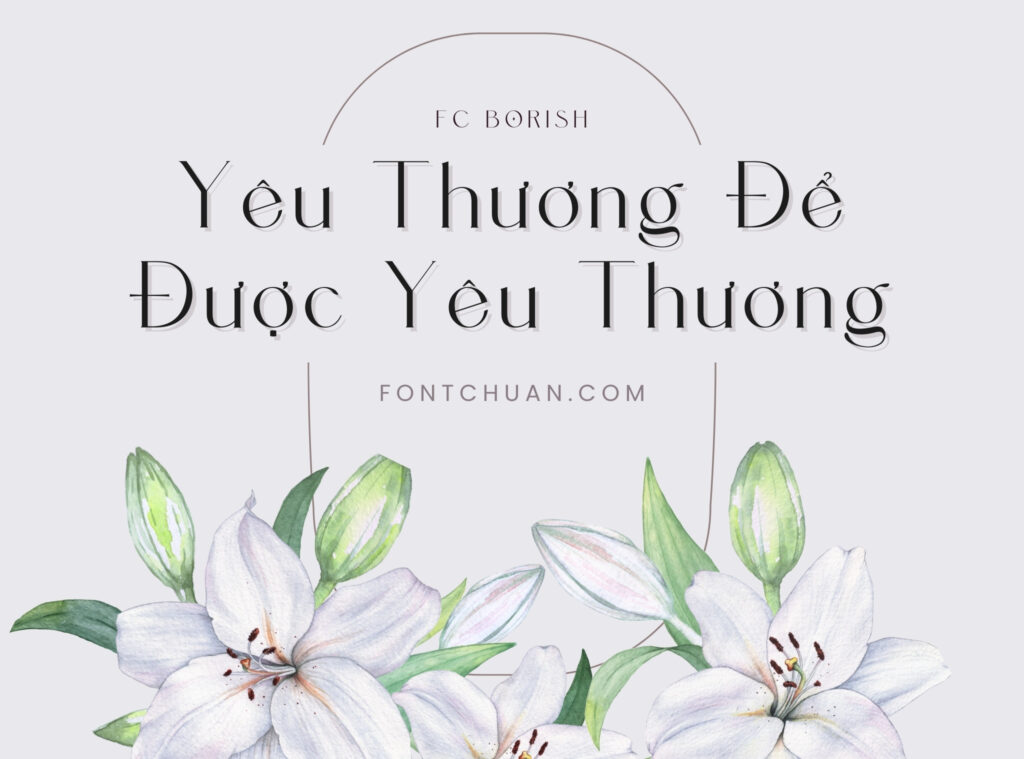
Borish là một font chữ serif thanh lịch và hiện đại, được thiết kế bởi Saemooncreative và phát hành vào khoảng tháng 6 năm 2024. Với các đường nét mảnh mai và những đường cong hài hòa, Borish mang đến cho thiết kế của bạn sự hoàn hảo và tinh tế. Font này hỗ trợ đa ngôn ngữ, bao gồm tiếng Anh, Pháp, Đức, Ý, Thụy Điển và nhiều ngôn ngữ khác, giúp người dùng dễ dàng ứng dụng trong các dự án quốc tế. Bên cạnh các ứng dụng chuyên nghiệp, Borish cũng có thể được sử dụng như một Font Lễ hội, mang lại không khí vui tươi, rực rỡ cho các poster, thiệp mời, banner sự kiện hoặc các ấn phẩm đặc biệt.
Font FC Borish được việt hóa bởi Font Chuẩn hỗ trợ đầy đủ tiếng Việt mà lại được tải về miễn phí, mang lại trải nghiệm mượt mà khi sử dụng cho cộng đồng thiết kế Việt Nam.
Không giống với phong cách phiên bản trên thị trường có thể có phí. Về đặc điểm thiết kế, FC Borish cố gắng giữ lại cấu trúc và đường nét của font gốc, sở hữu cấu trúc chữ rõ ràng, độ tương phản cao và độ dày đồng đều, tạo cảm giác cân đối và dễ đọc. Các đường nét mượt mà và tinh tế của font này làm nổi bật sự chuyên nghiệp và sang trọng.
Borish lý tưởng để sử dụng trong các dự án thiết kế thương hiệu, bao bì sản phẩm cao cấp, bất động sản và các ấn phẩm biên tập. Ngoài ra, font này còn phù hợp với các lĩnh vực như Spa thẩm mỹ, thời trang, mỹ phẩm, sự kiện cưới và truyền thông, nơi cần sự kết hợp giữa phong cách cổ điển và hiện đại.